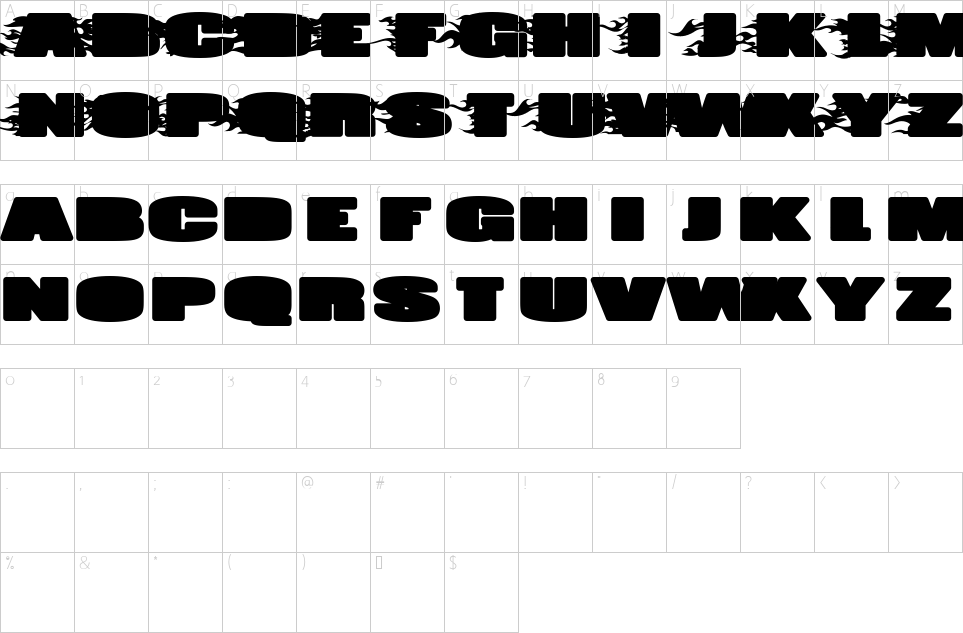
A fonte Jumbo Burn é uma excelente escolha para designers gráficos e escritores que buscam um estilo moderno e atraente para seus projetos. Ela foi criada por uma designer desconhecida, mas sua estética espalhafatosa e vibrante certamente chama a atenção. Jumbo Burn traz uma textura única e colorida que pode ser usada para destacar texto em qualquer tipo de layout. Este design foi baixado 21,159 vezes, mostrando sua popularidade entre os criadores de conteúdo digital. A fonte é ideal para projetos web, títulos e headlines, ou até mesmo para adicionar um toque de personalidade em designs de cartões de agradecimento ou cartas. Se você está procurando uma fonte única que pode destacar seus projetos, Jumbo Burn é uma ótima opção.